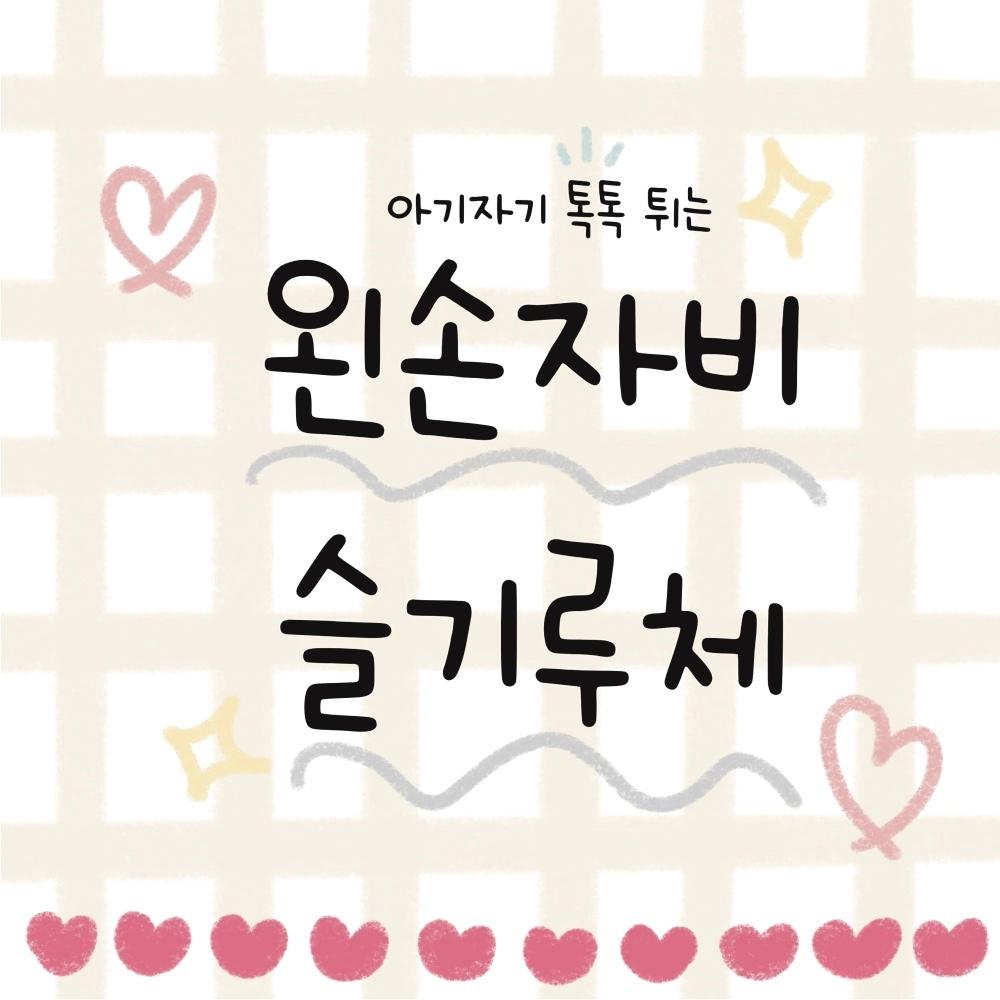
그리운 왼손자비슬기루체
Griun LEFT SG
그리운 왼손자비슬기루체 소개
그리운 왼손자비슬기루체(Griunn LEFT SG)는 저만의 손글씨 속 톡톡 튀는 강점들을 표현한 폰트입니다. 저는 어린이집 교사로, 환경구성·메모·행사·다이어리 등 다양한 곳에서 제 손으로 글을 표현하는 일이 자주 있었습니다. 아기자기한 내 글씨체를 나 뿐 아니라, “다양한 곳에서 여러 사람들이 이모저모 사용할 수 있었으면 좋겠다.” 라고 생각해 직접 한글자 한글자 신중히 담아 표현했습니다. 왼손자비슬기루체로 아기자기한 다꾸, 노트필기, 이미지 제작 등 다양하게 활용해보시길 바랍니다 :)